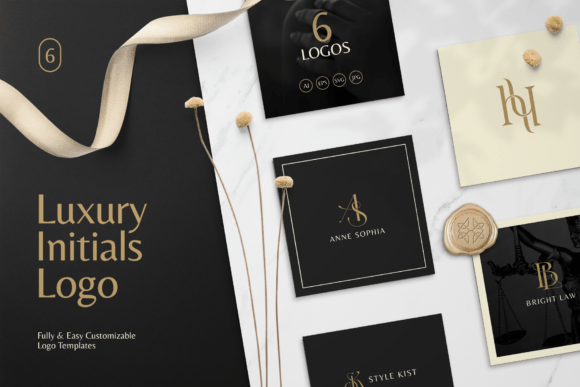
INITIALS LOGO - Luxury Initials Logos
INITIALS LOGO - Luxury Initials Logos์ ๊ฐ์ ๊ณ ํ์ง ์์ฐ์ ์ฐพ๊ณ ์๋ค๋ฉด ์ด ํ๋ฆฌ๋ฏธ์ ํจํค์ง๋ ์ฐฝ์์ ์ธ ํ๋ก์ ํธ๋ฅผ ์ํ ํ์์ ์ธ ์ ํ์ ๋๋ค.
์ ๋ฐํ๊ฒ ์ ์๋ INITIALS LOGO - Luxury Initials Logos๋ ๊น๋ํ ๋ฒกํฐ, ๋ถ๋๋ฌ์ด ํ์ดํฌ๊ทธ๋ํผ ๋ฐ ์์ฌํ ์ ์๋ ์์ ์ฉ ๋ผ์ด์ ์ค๋ฅผ ์ ๊ณตํฉ๋๋ค.
POD(์ฃผ๋ฌธํ ์ธ์) ์ ํ, ๊ฒฐํผ์ ์ด๋์ฅ ๋๋ ์์ ๋ฏธ๋์ด ๊ทธ๋ํฝ์ ๋ง๋ค ๋ INITIALS LOGO - Luxury Initials Logos๋ ์ด์์ ์ธ ์ ํ์ ๋๋ค.